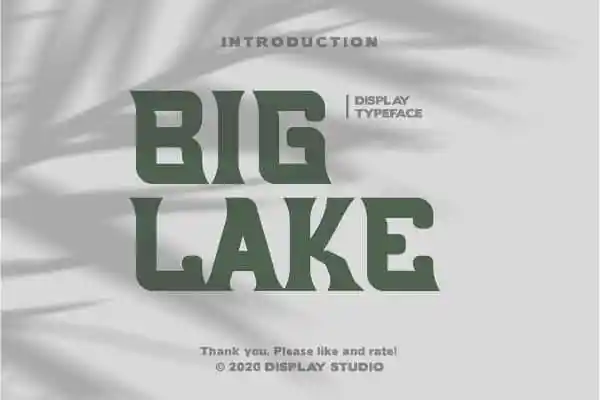
Introduzimos Big Lake Display Font, uma fonte vintage limpada inspirada na arte manual original. É perfeitamente adaptável para criar seus produtos incríveis e é adequado para designs de rótulos, logotipos, selos, camisetas, cartazes, cartões de agradecimento, ataques ou qualquer coisa que tenha um estilo vintage. Se você ama esse design, certamente vai se encantar com Big Lake Display Font. Suas duas versões diferentes garantem que ela encaixe perfeitamente em uma variedade de projetos, tornando-a uma opção ótima para quem busca adicionar um toque especial a sua criação. Esse é mais do que apenas uma fonte: ele é uma maneira de dar vida à sua arte e fazer seu design se destacar na multidão.